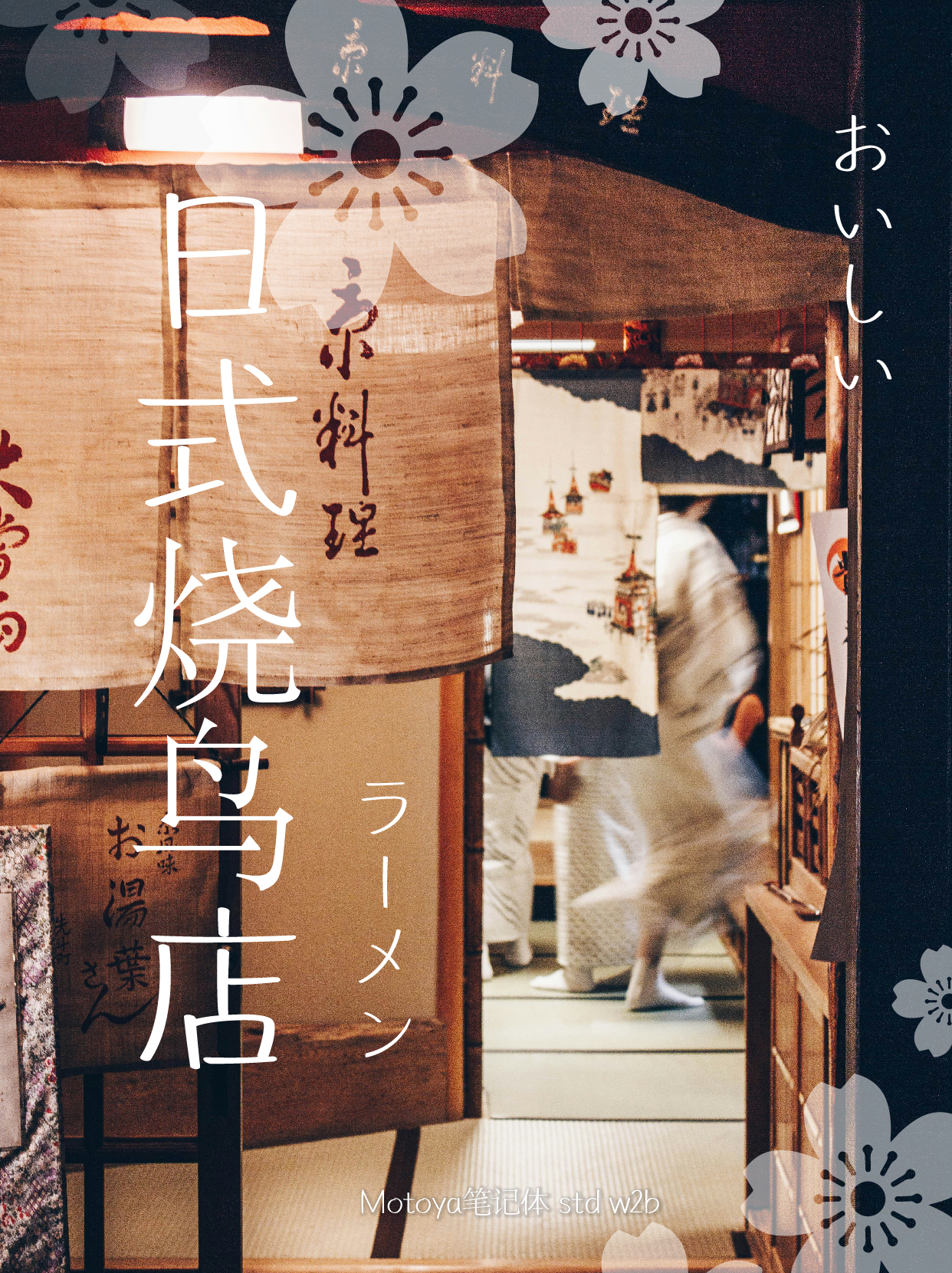
Note的设计是,在挥洒笔的时候产生的线的粗细不等,将纯手写作为特有的特征,曲线表现会有很多需要注意的地方,另外,写完横线后直接连着写出竖线的时候,会出现的连笔间若干间隙等,强调了手写字特有的“人情味、温馨”的字体。Note所具有的“人情味”与纸质媒体的搭配也很好,无论是给谁的信息留言还是简短的评语,都能表现出温柔和温馨,能制作出充满感情的文章。